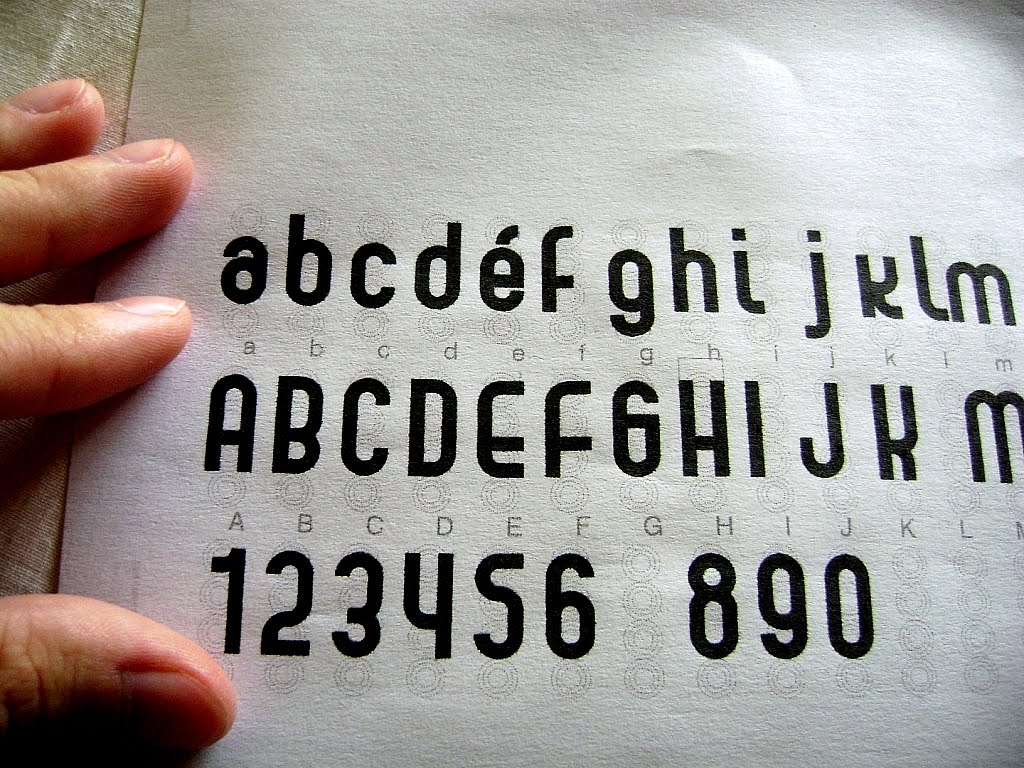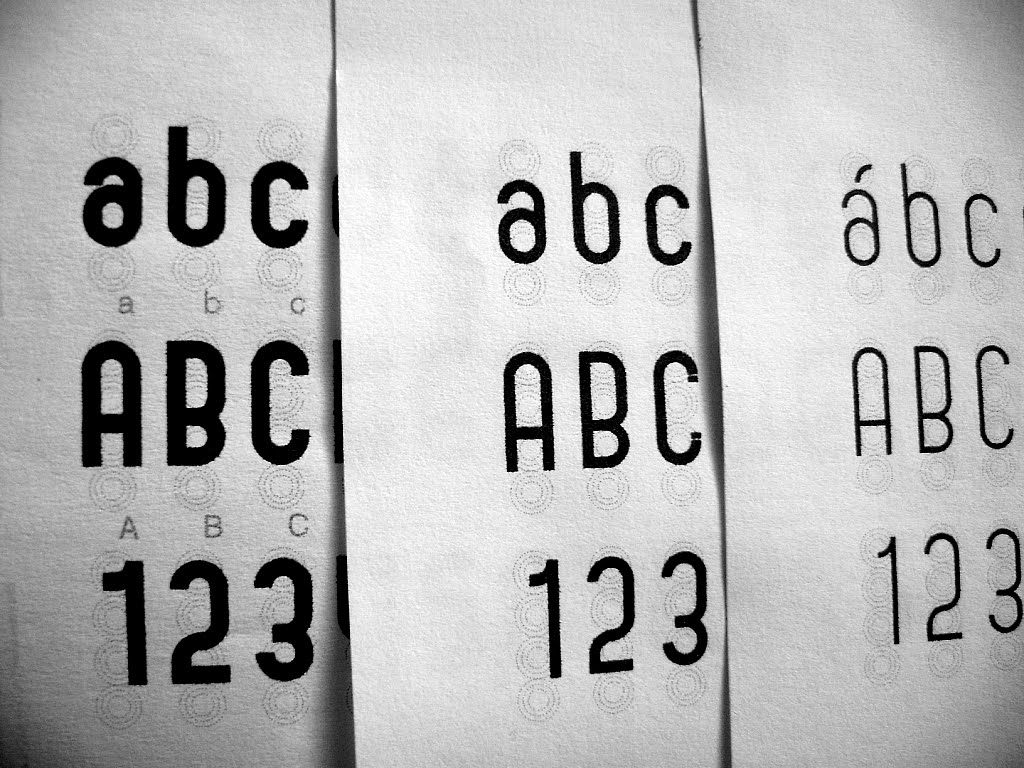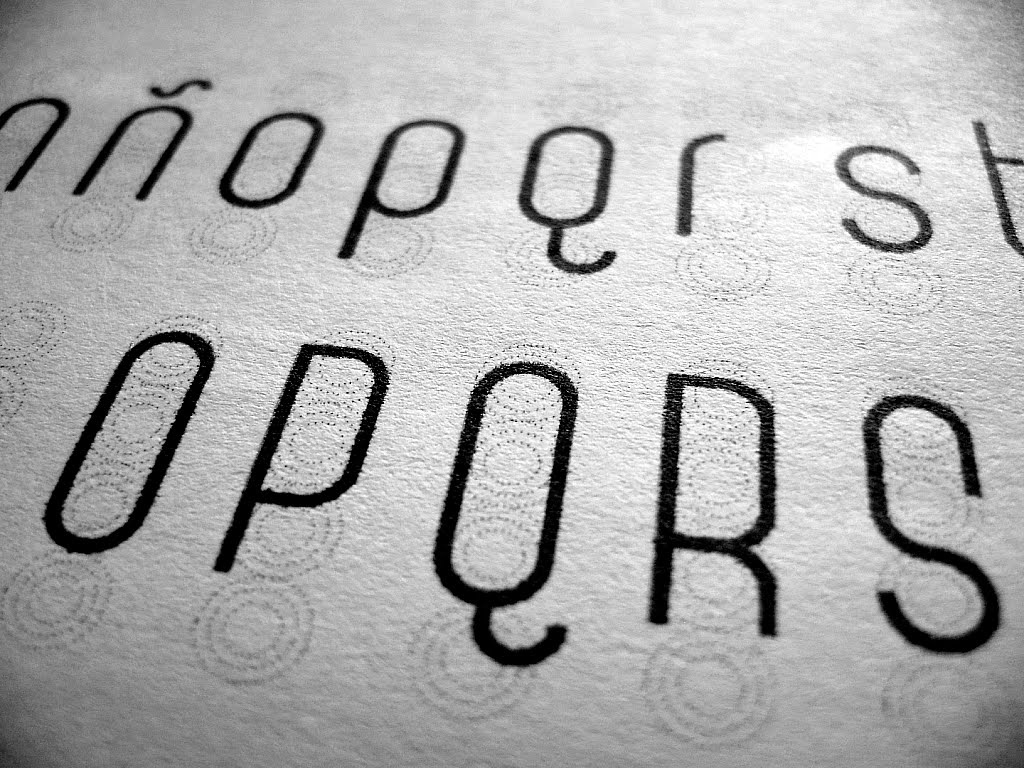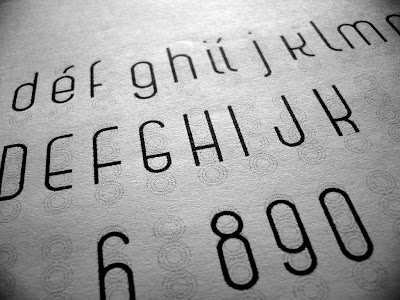
Tipografía Trescirc – Parte 3
Trunbet, el nombre de mi futura tipografía sigue avanzando. Hoy realicé unas impresiones para corregir «errores» en las formas; al realizar estas impresiones puedo observar mejor algunas cuestiones que en pantalla quizás paso por alto.
Algunas mayúsculas y algunos números me están dando algunos problemas; sin embargo esto es bueno porque me permite identificar cuales son las variantes y las constantes de la tipografía. Todavía no he comenzado con las miscelaneas ni signos de puntuación.
Como había comentado anteriormente, esta familia se compone de tres variables de peso: light, medium y bold.
En las imágenes pueden ver algo del proceso de creación de la tipografía, y la cuadrícula utilizada.